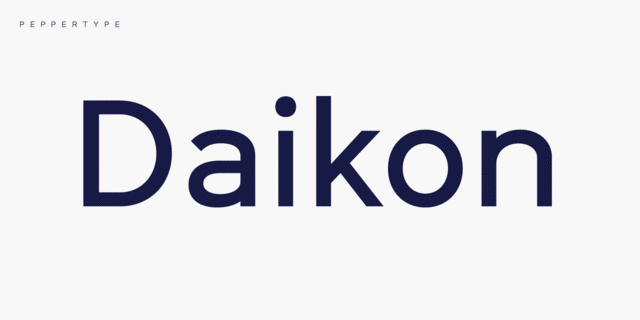
Daikon – это полуоткрытый геометрический гротеск с богатой языковой поддержкой, включая кириллицу, различные функции OpenType и несколько наборов цифр. Чистота и удобочитаемость этого шрифтового семейства позволяет использовать его как для акциденции, так и для текстов любого размера. Шрифт разработал Олег Лищук в 2020 году.
минималистичный, четкий, деликатный, чистый, легкий, прохладный, свежий, модный, тонкий, современный, лаконичный, ясный, ровный, понятный, качественный, городской, логичный, точный, глобализированный, глобалистичный, стеклянный, острый, хрупкий, холодный, статичный, худой
Хит 1930-х Хит 2010-х Этот шрифт в логотипах:
Clubhouse, airbnb